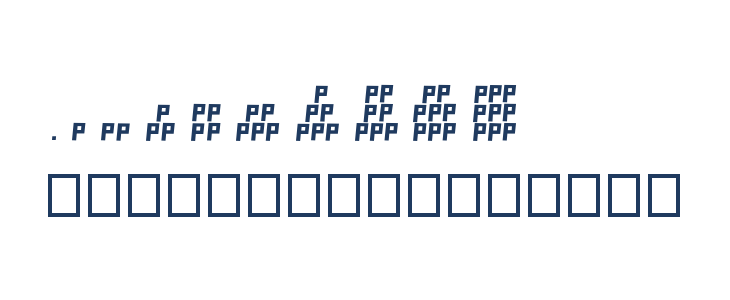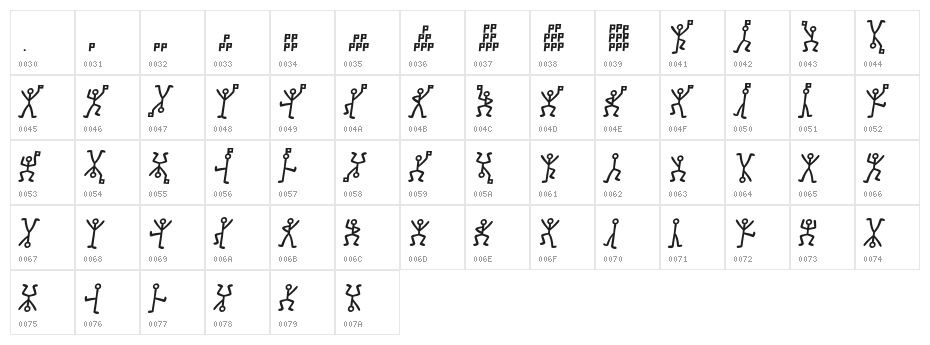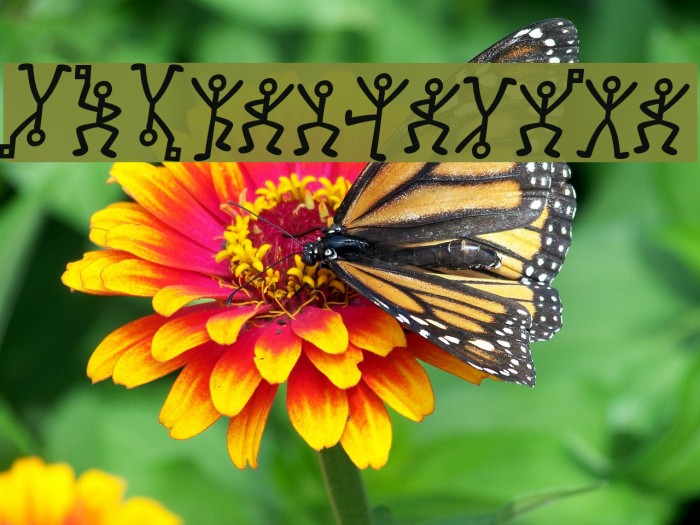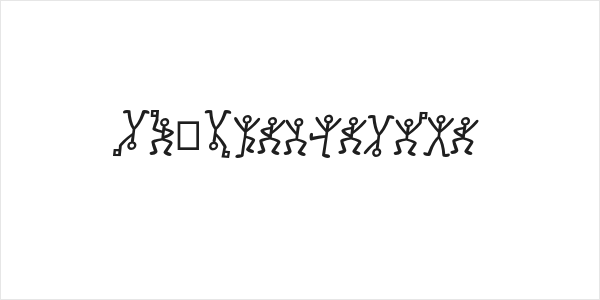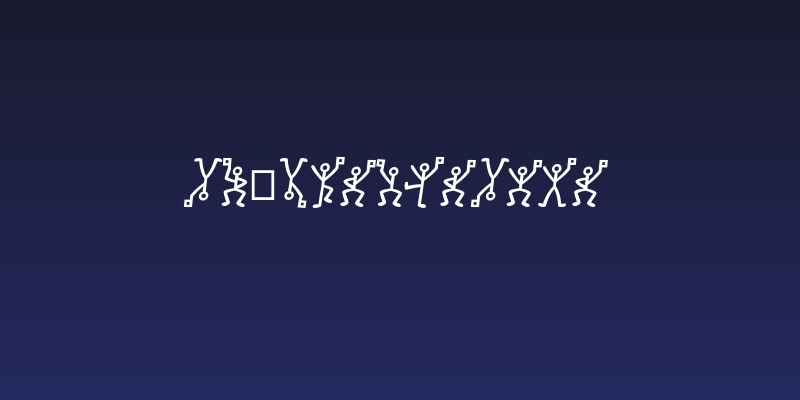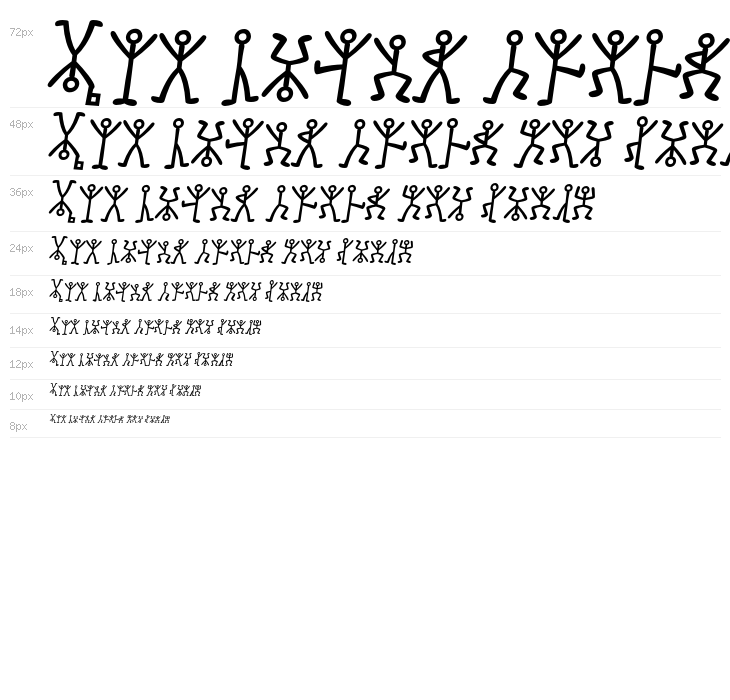
GL-DancingMen Font
| Vorgeschlagene Projekte | Ideal for party invitations, children's books, playful branding, or any project needing a fun and lively touch. |